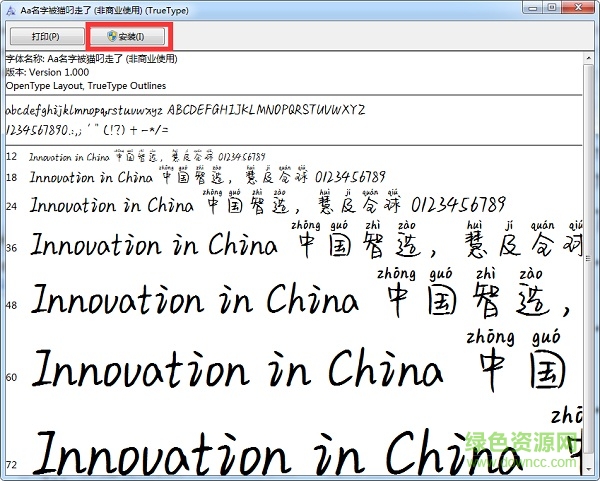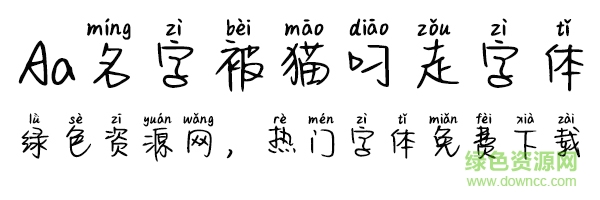
名字被貓叼走了字體ttf是aa字庫推出的免費(fèi)資源。這其實(shí)就是一個拼音字體,字體比較卡通化,設(shè)計(jì)一些兒童宣傳海報(bào)非常適用。可以在多種主流系統(tǒng)上安裝使用!需要的用戶歡迎下載安裝。
名字被貓叼走了字體美觀有趣!在英文部分和數(shù)字、標(biāo)點(diǎn)部分就是一個單純的手寫字體,但是在漢字部分上標(biāo)注了該漢字的拼音!這款字體非常不錯,喜歡的用戶可以來綠色資源網(wǎng)免費(fèi)下載使用!